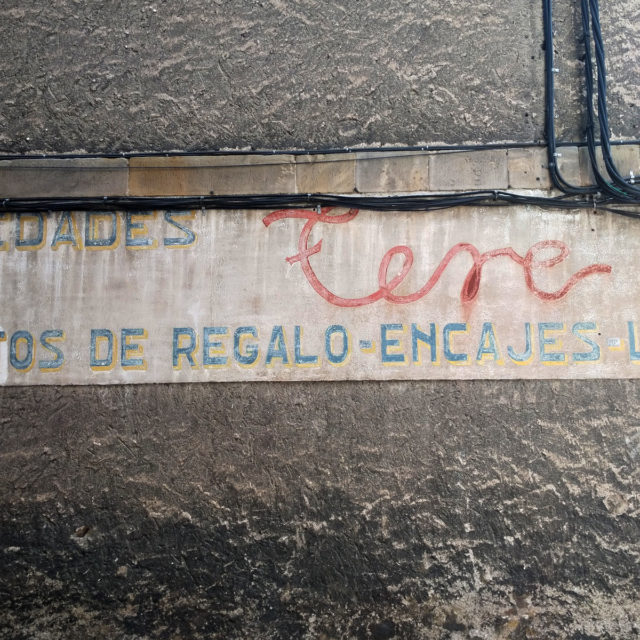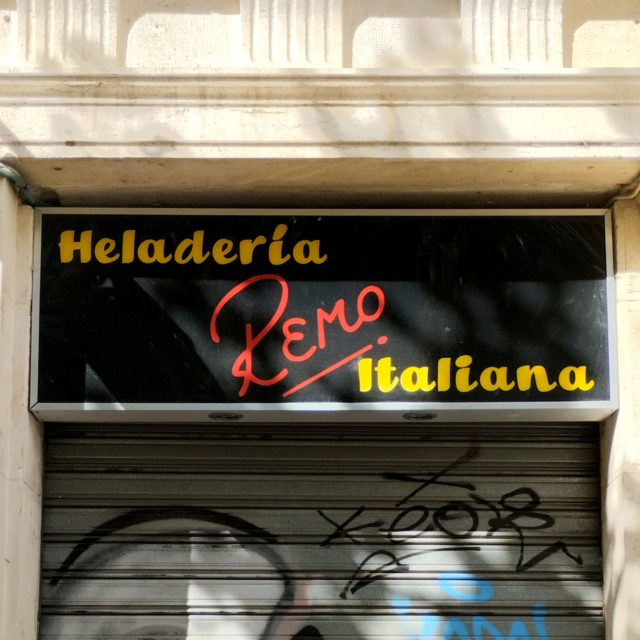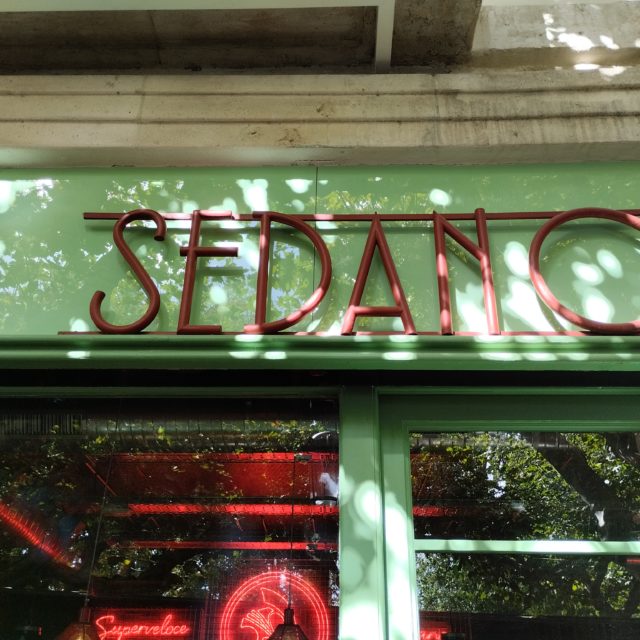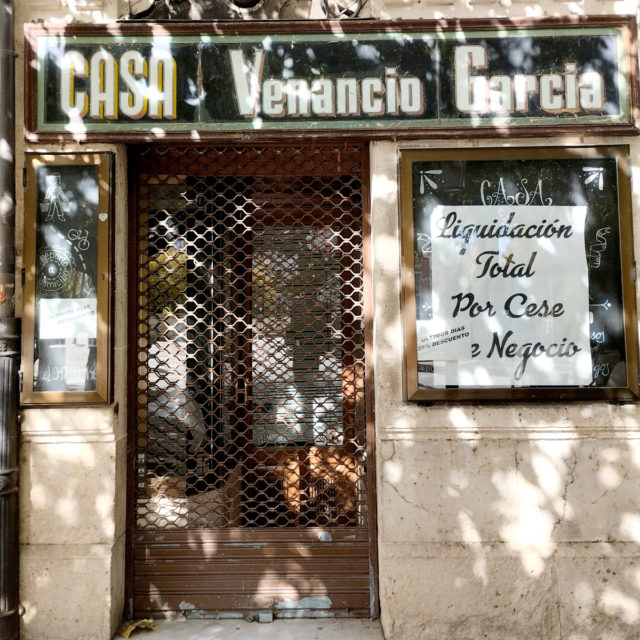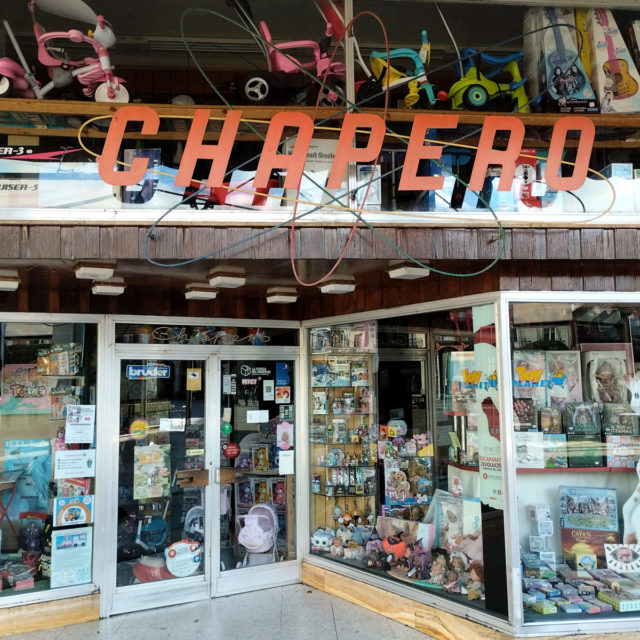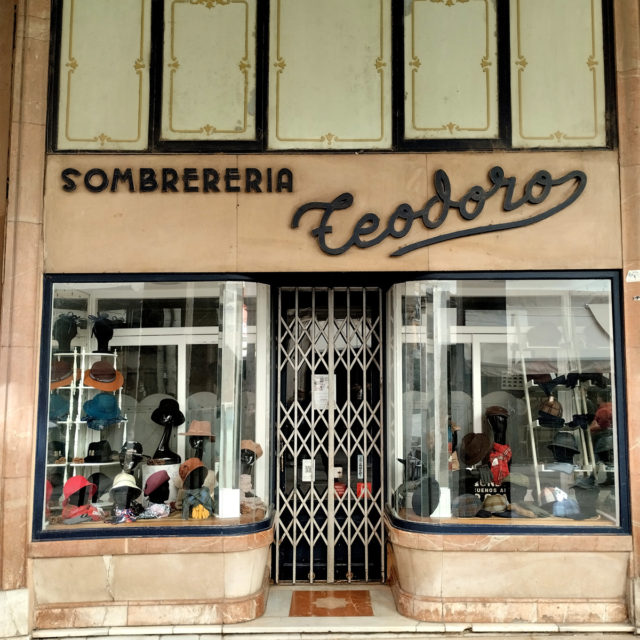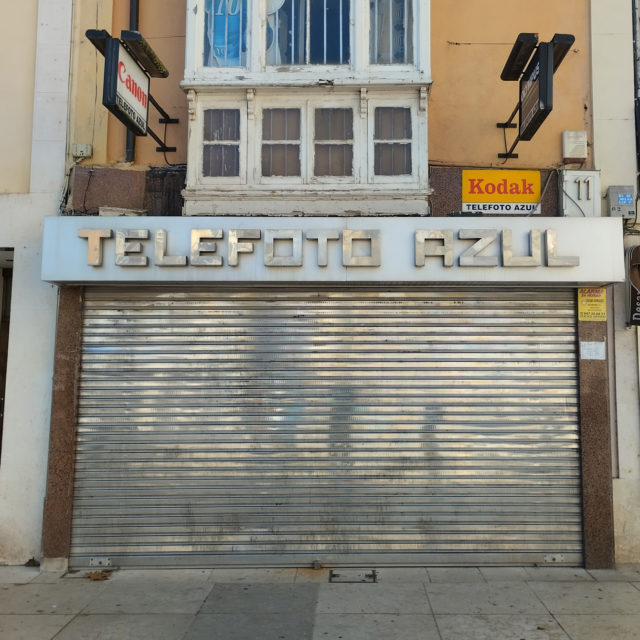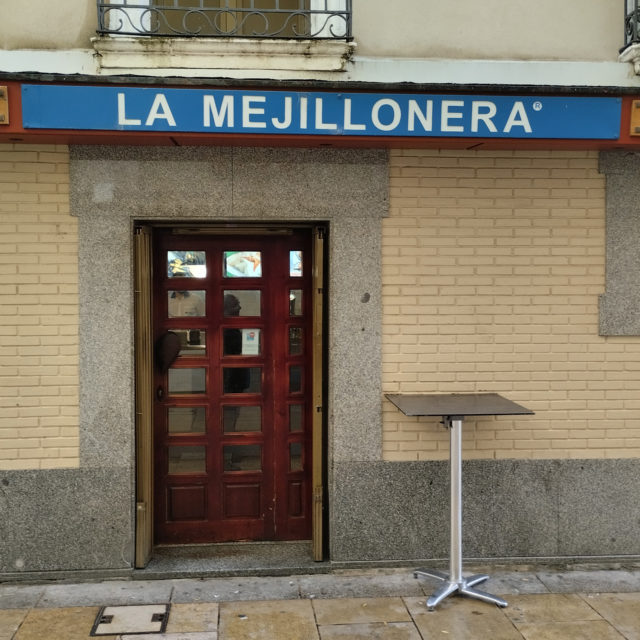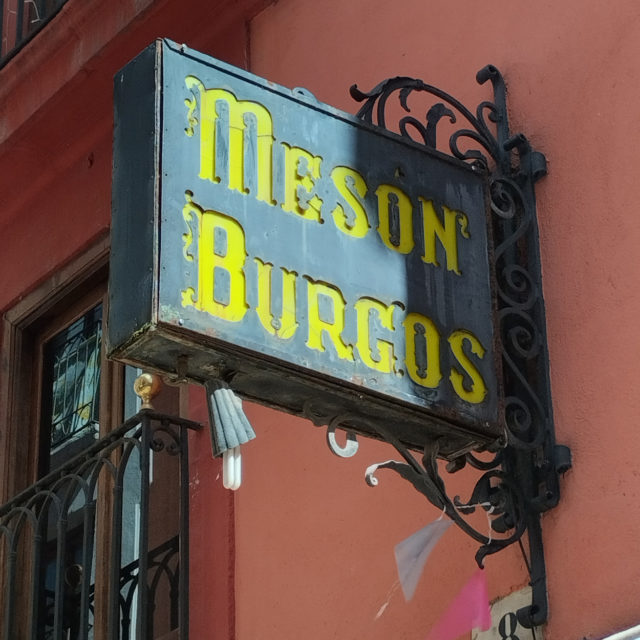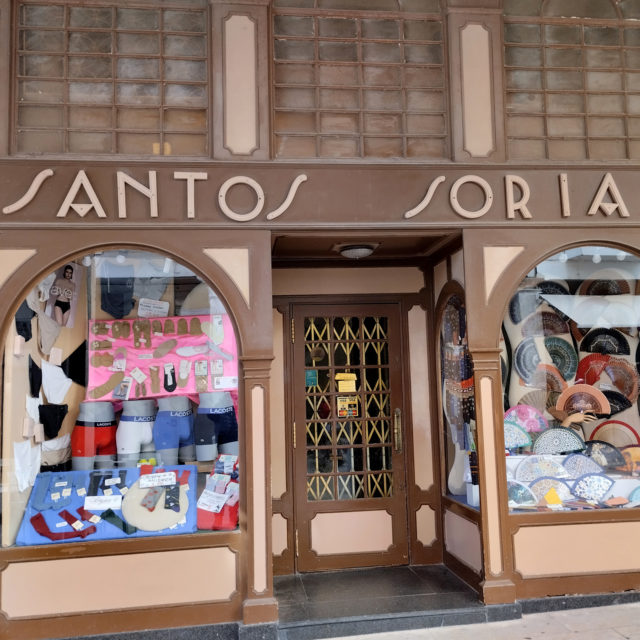
Paseo tipográfico por Burgos
Nota: Fijaros en «Sombrerería Teodoro» esa T. Es muy parecida a la que hay en Reinosa con «Novedades Tere». Que por cierto, también forma parte del poster del #36DaysOfType que hicimos este año.